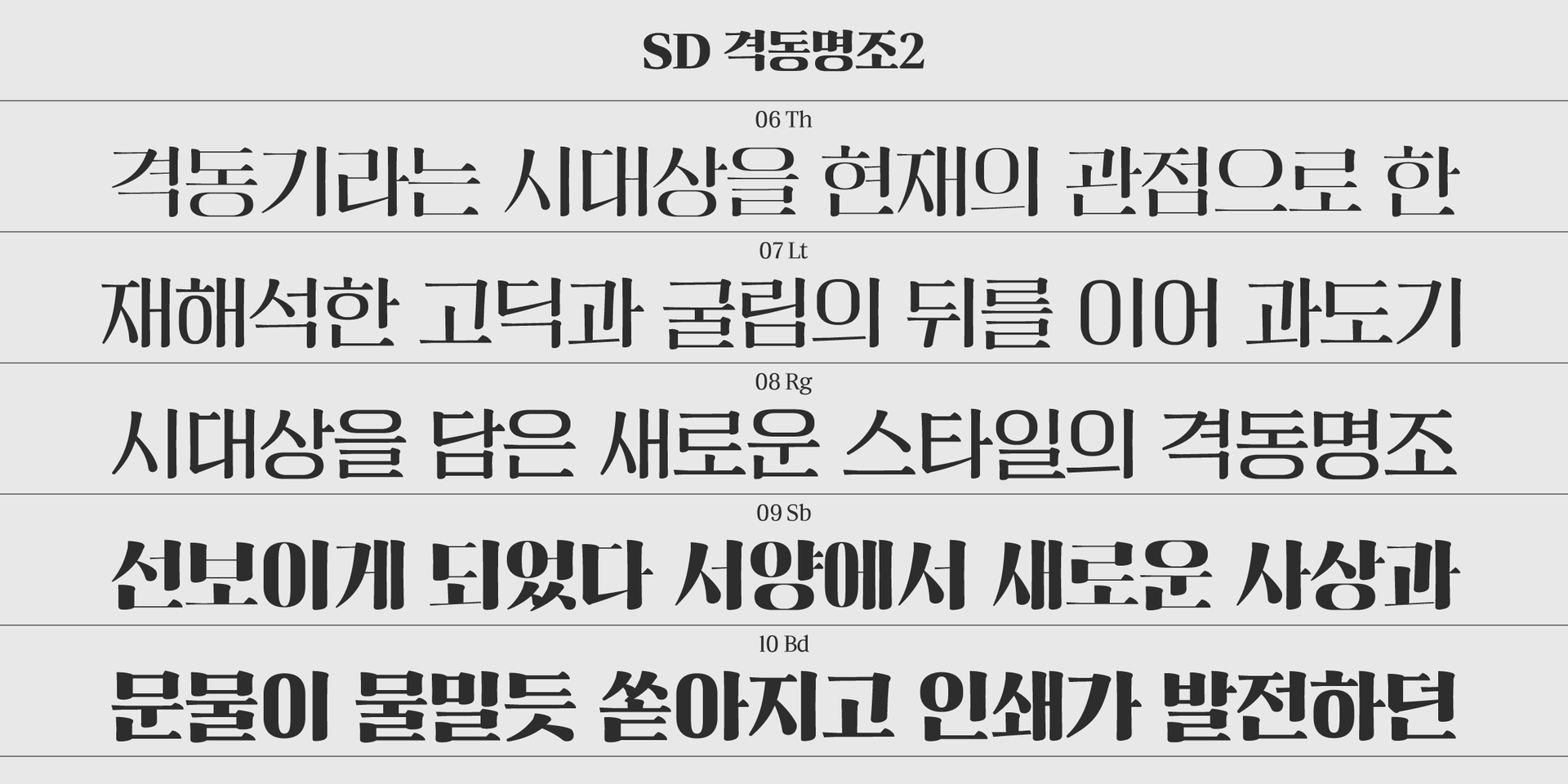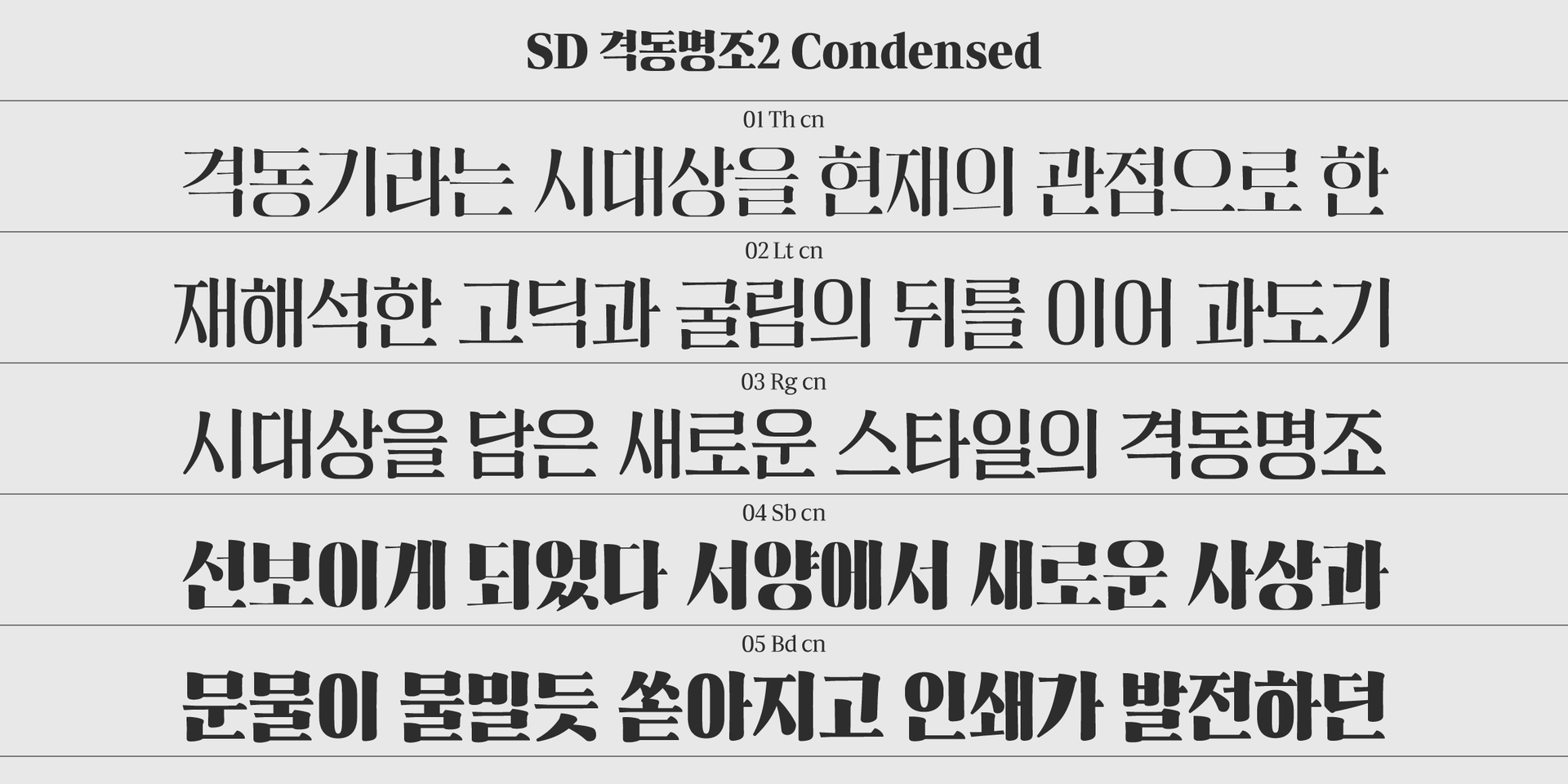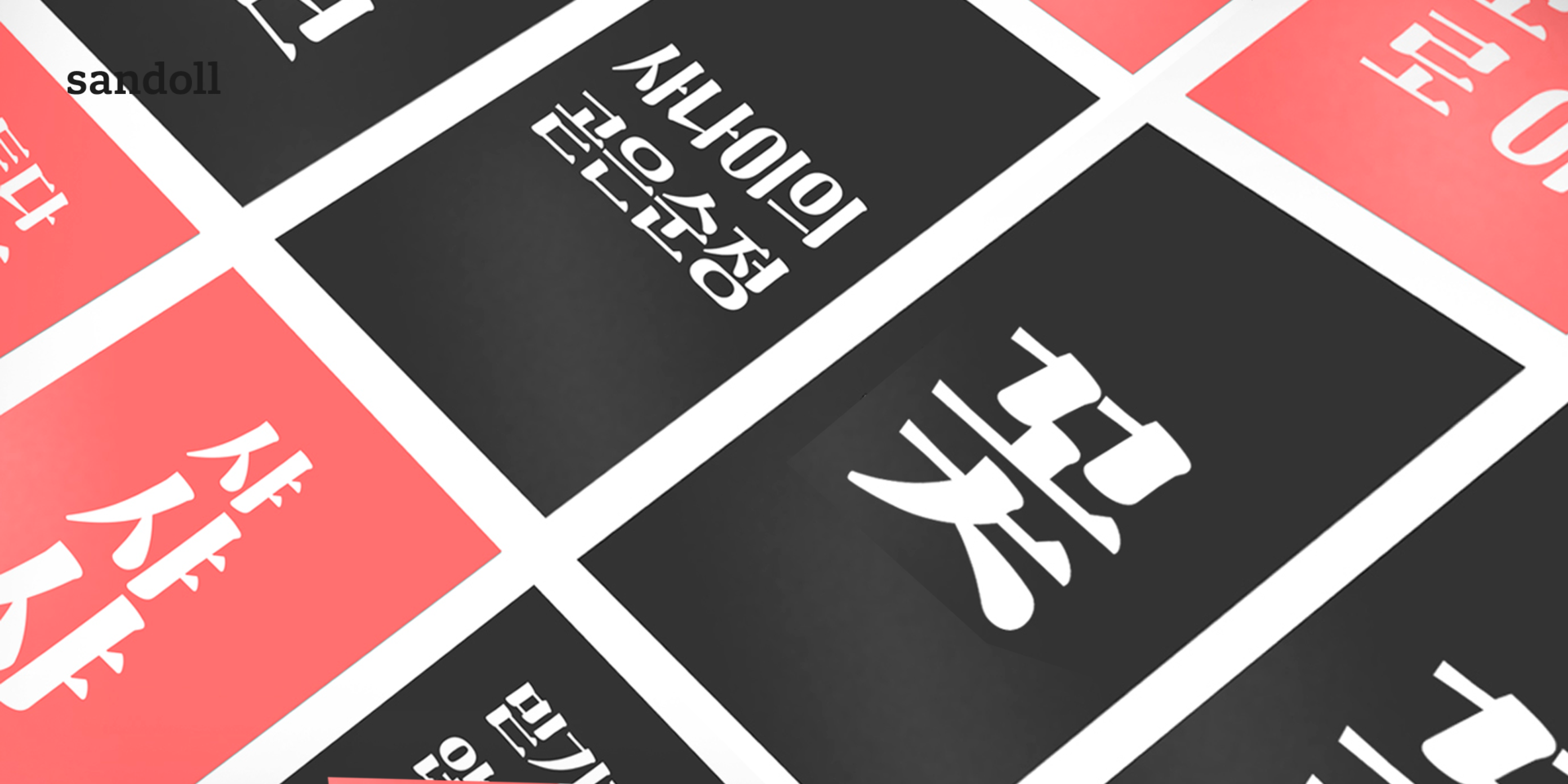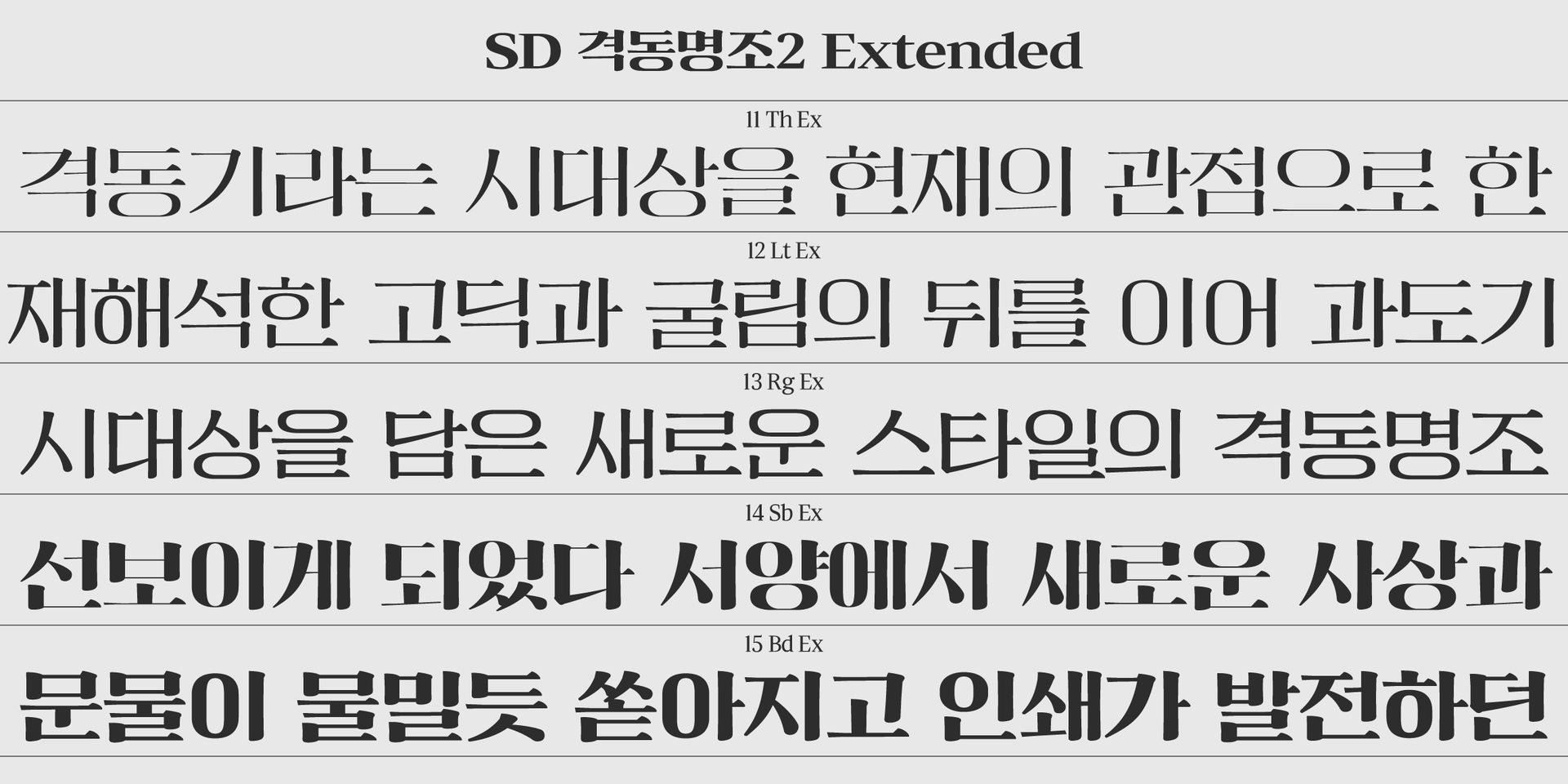
Sandoll 격동명조
산돌 격동명조는 격변하는 과도기적 시대상을 현대적 관점으로 재해석한 명조체 폰트이다.네모틀에 꽉차는 격동고딕과 같은 모듈을 갖고 있으며, 획을 끊어서 들어올려치는 한자 서예의 특징과 다소 경직된 내릿점으로 납활자의 물성을 표현한 부분이 인상적이다.